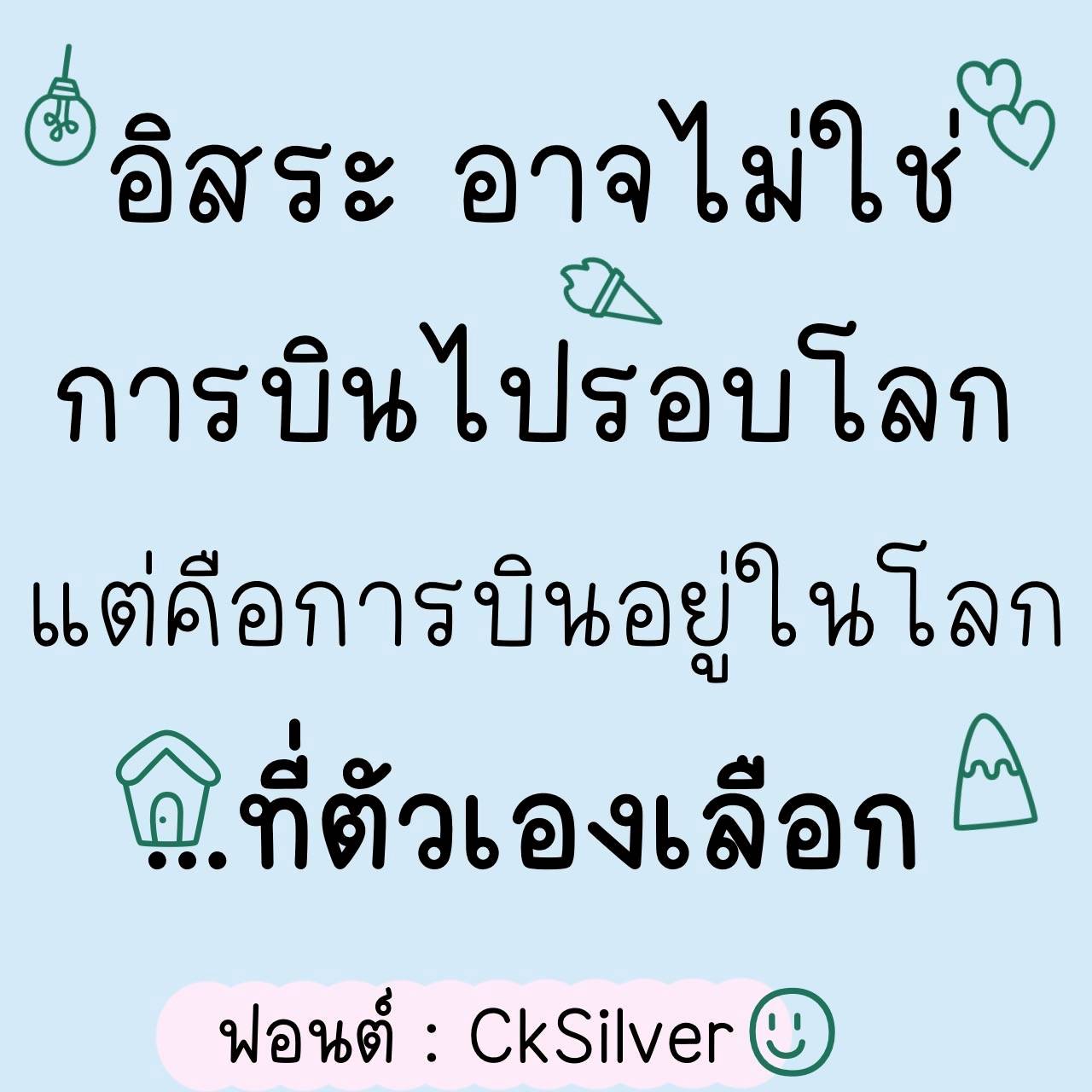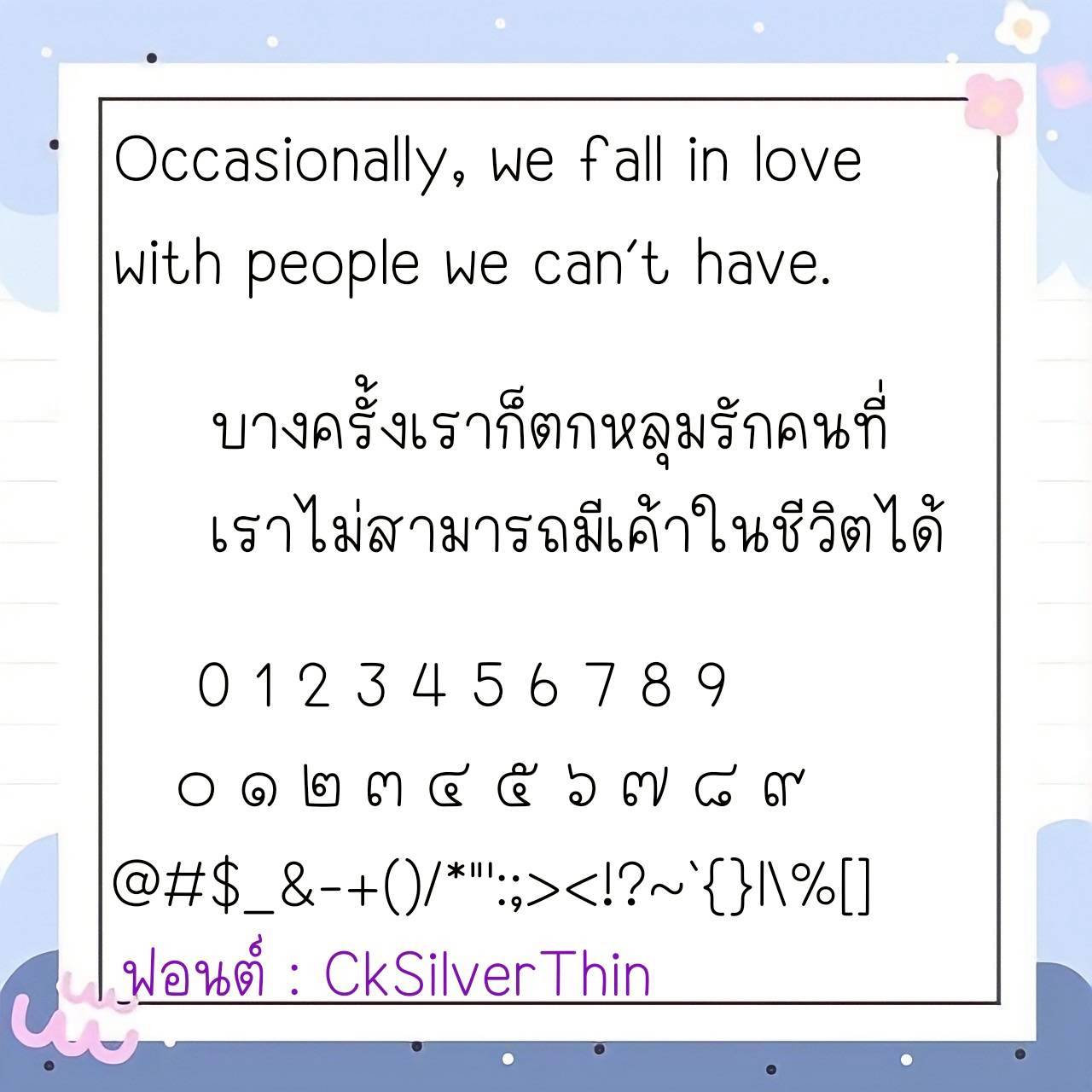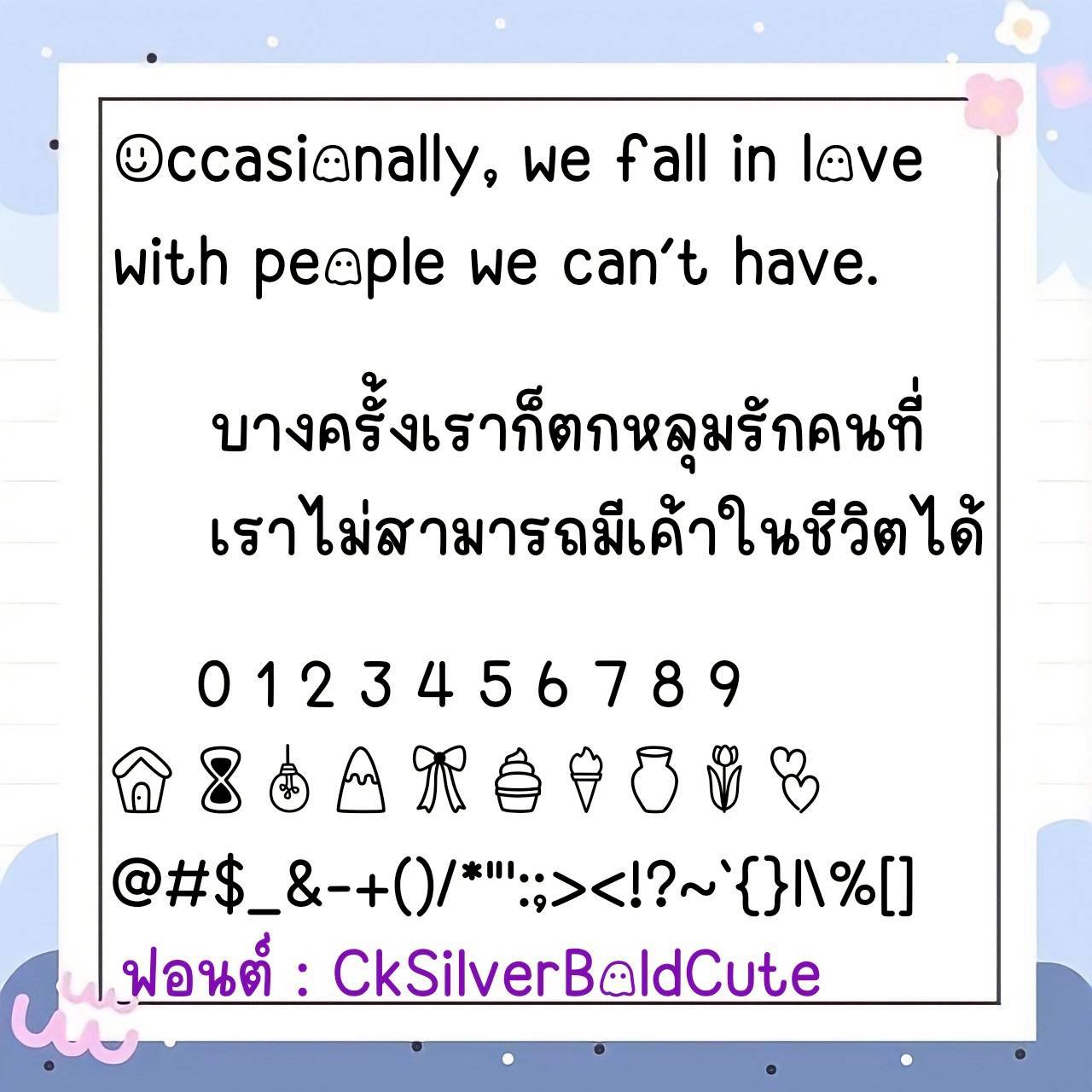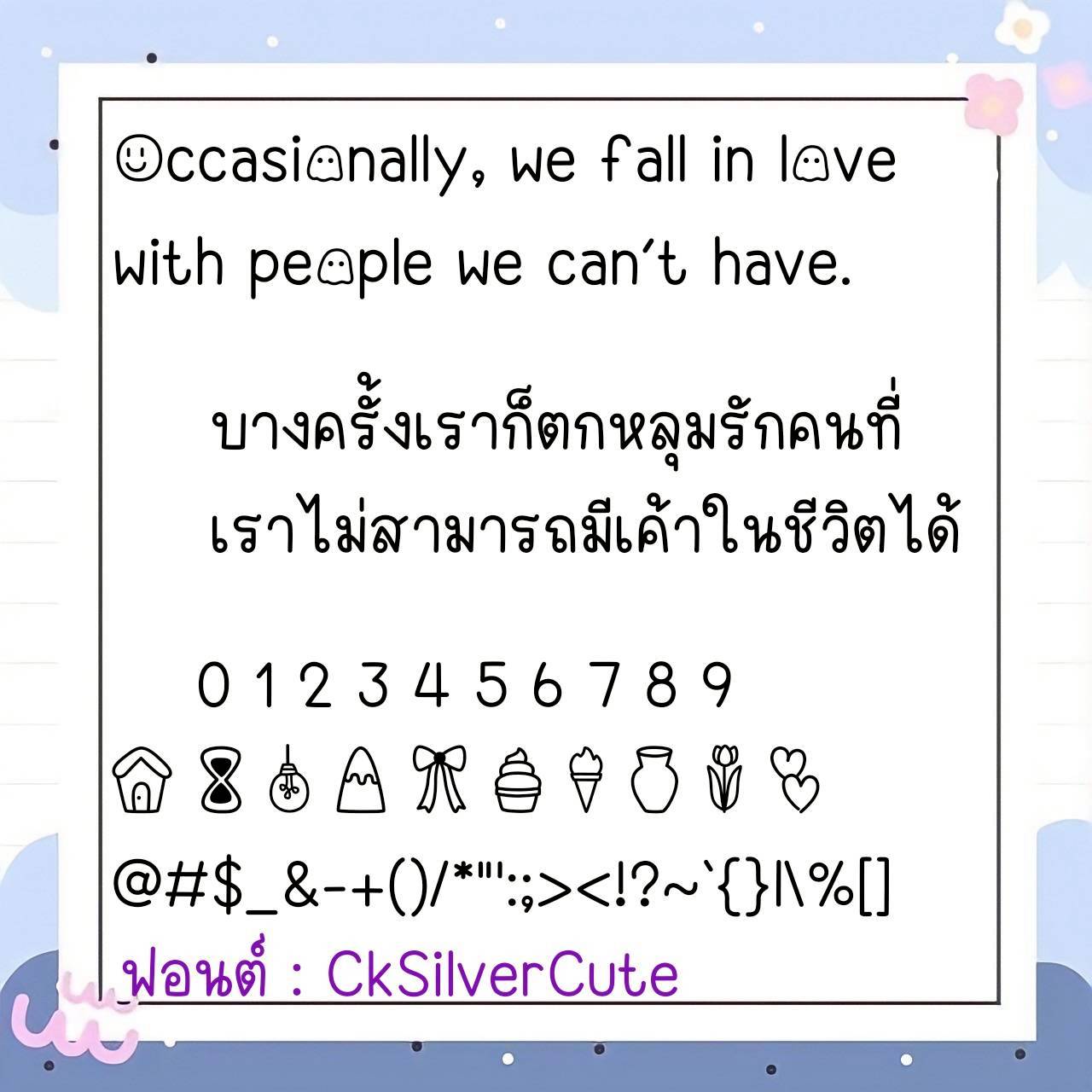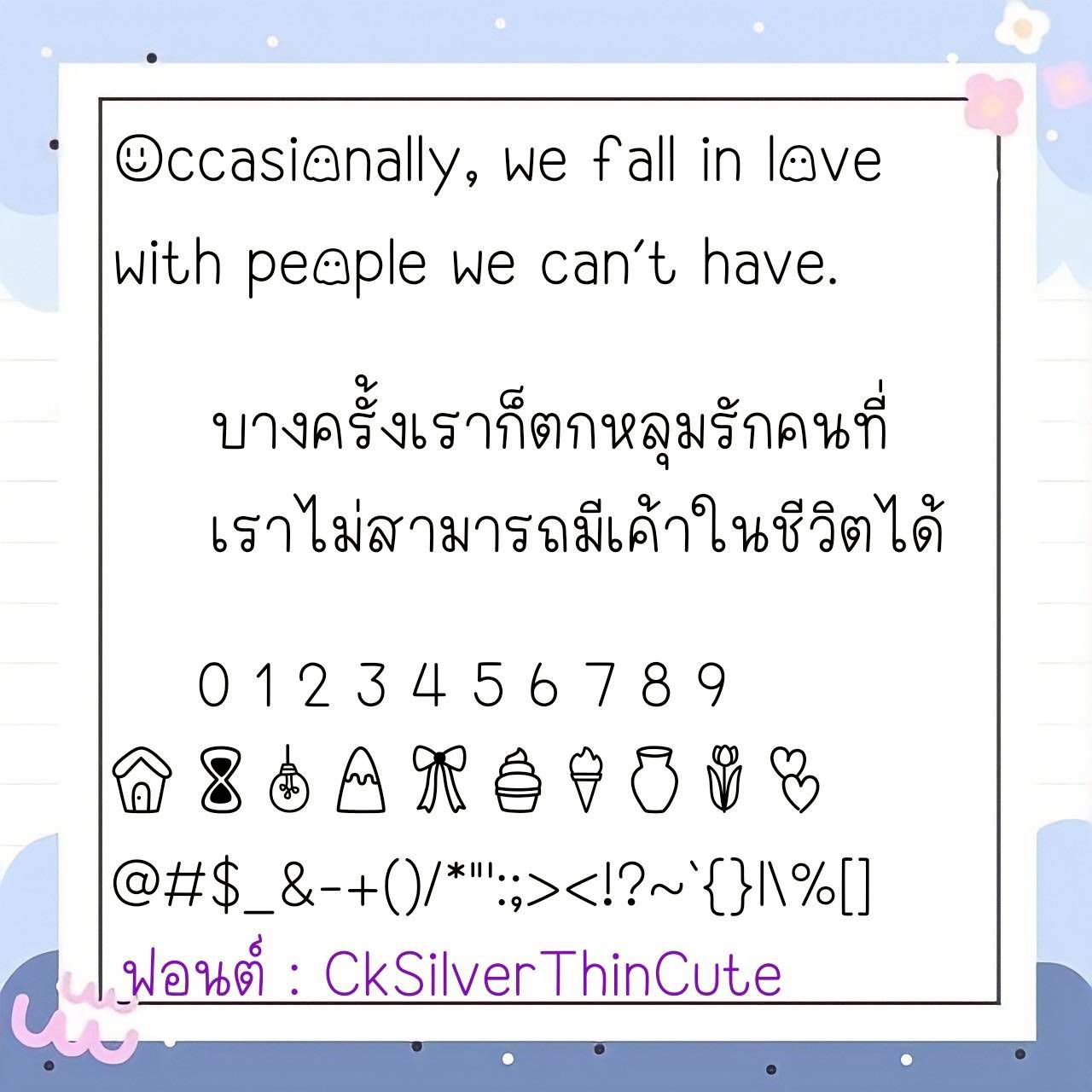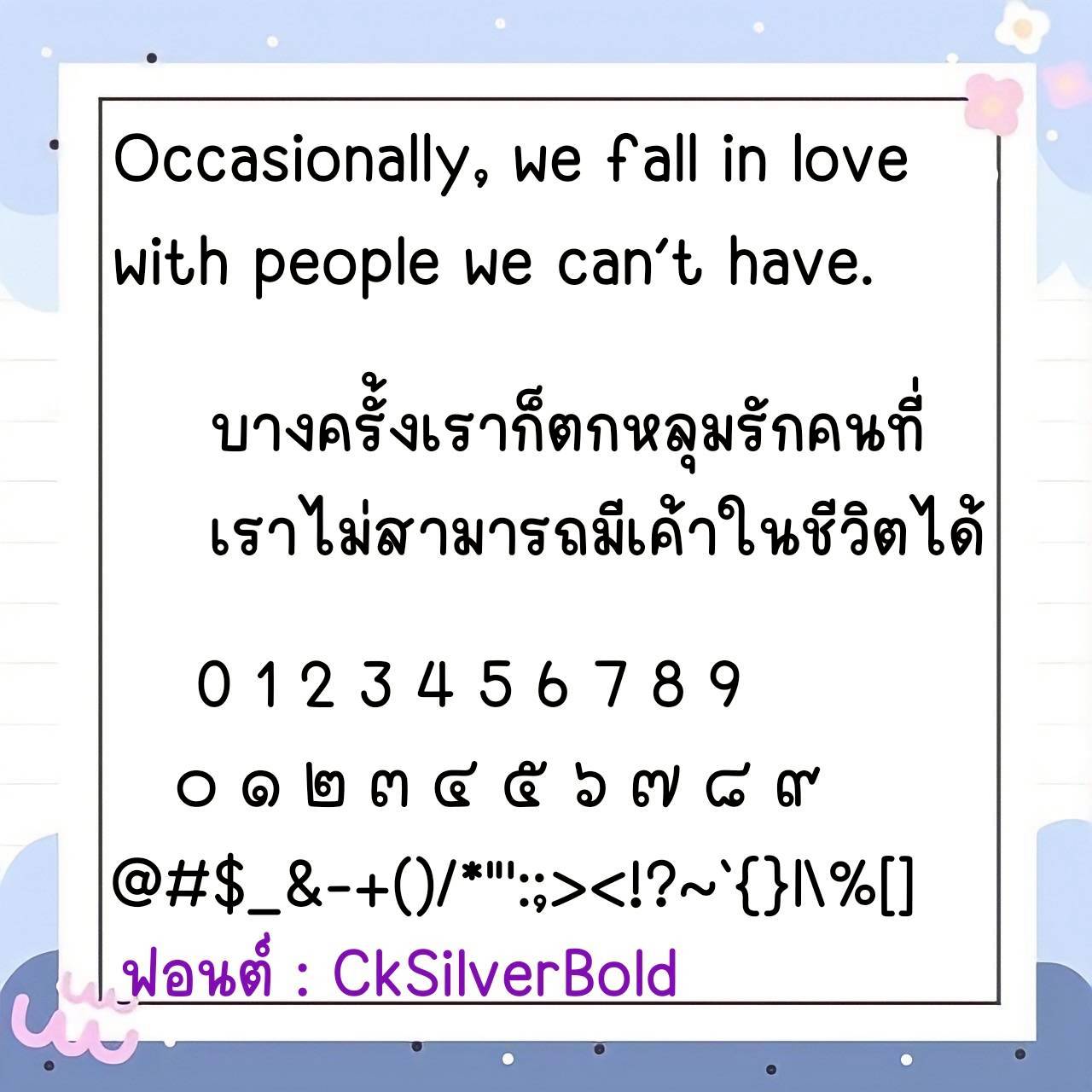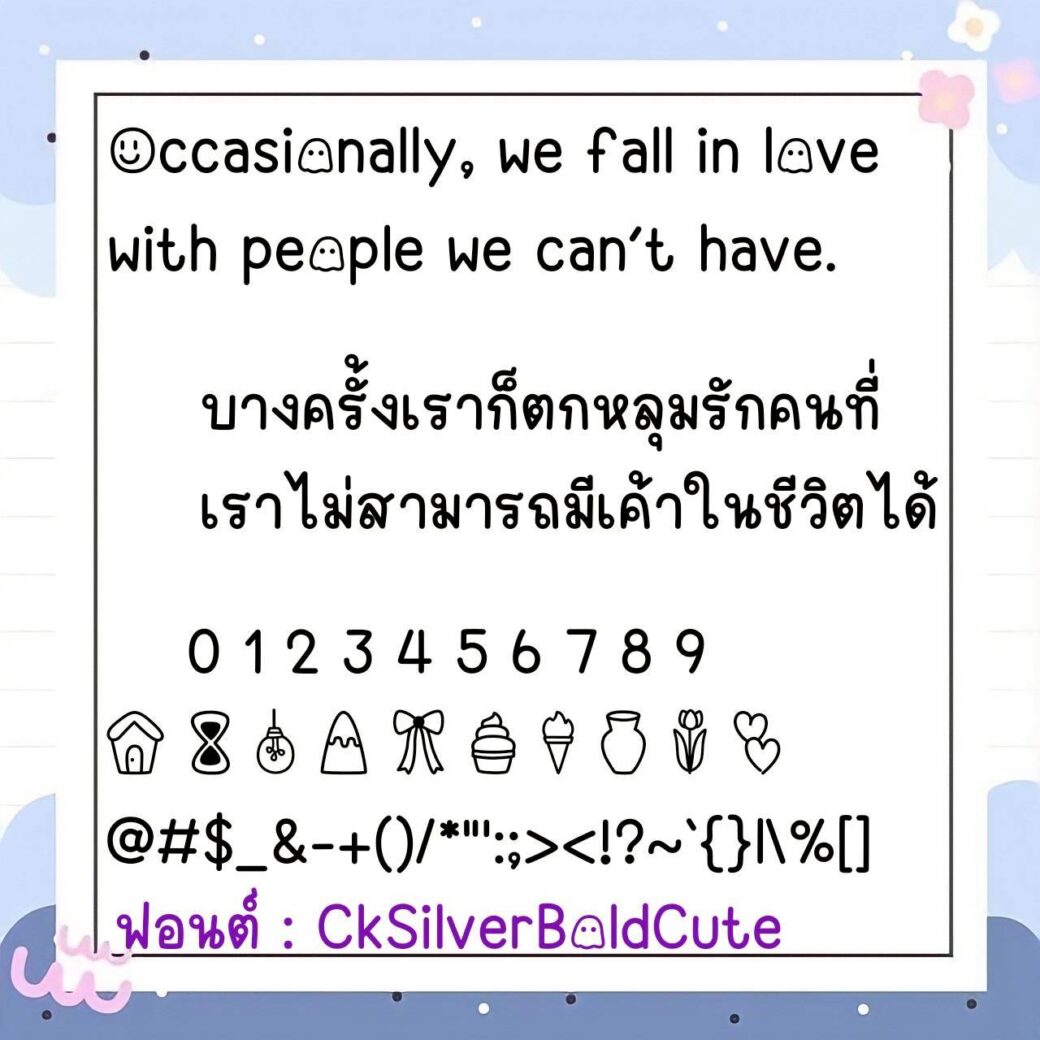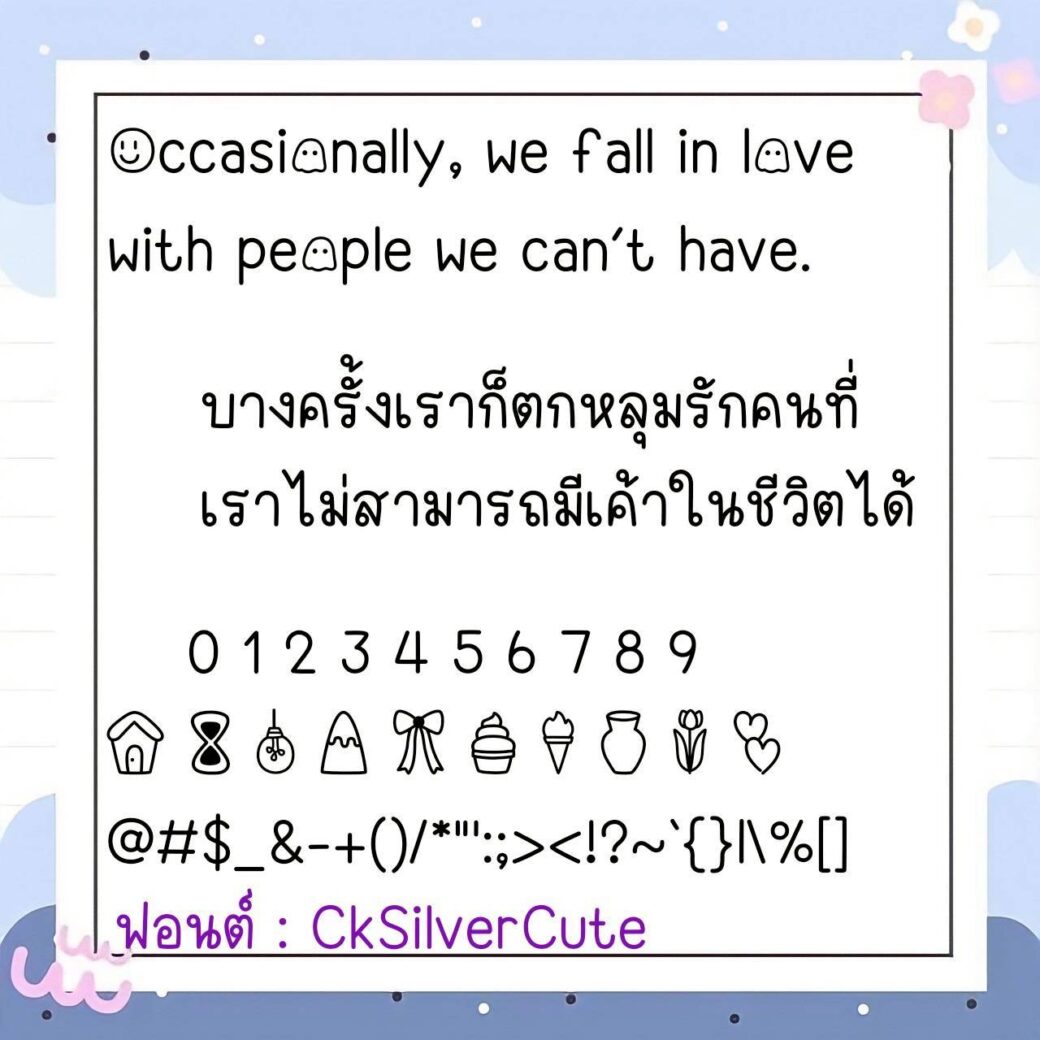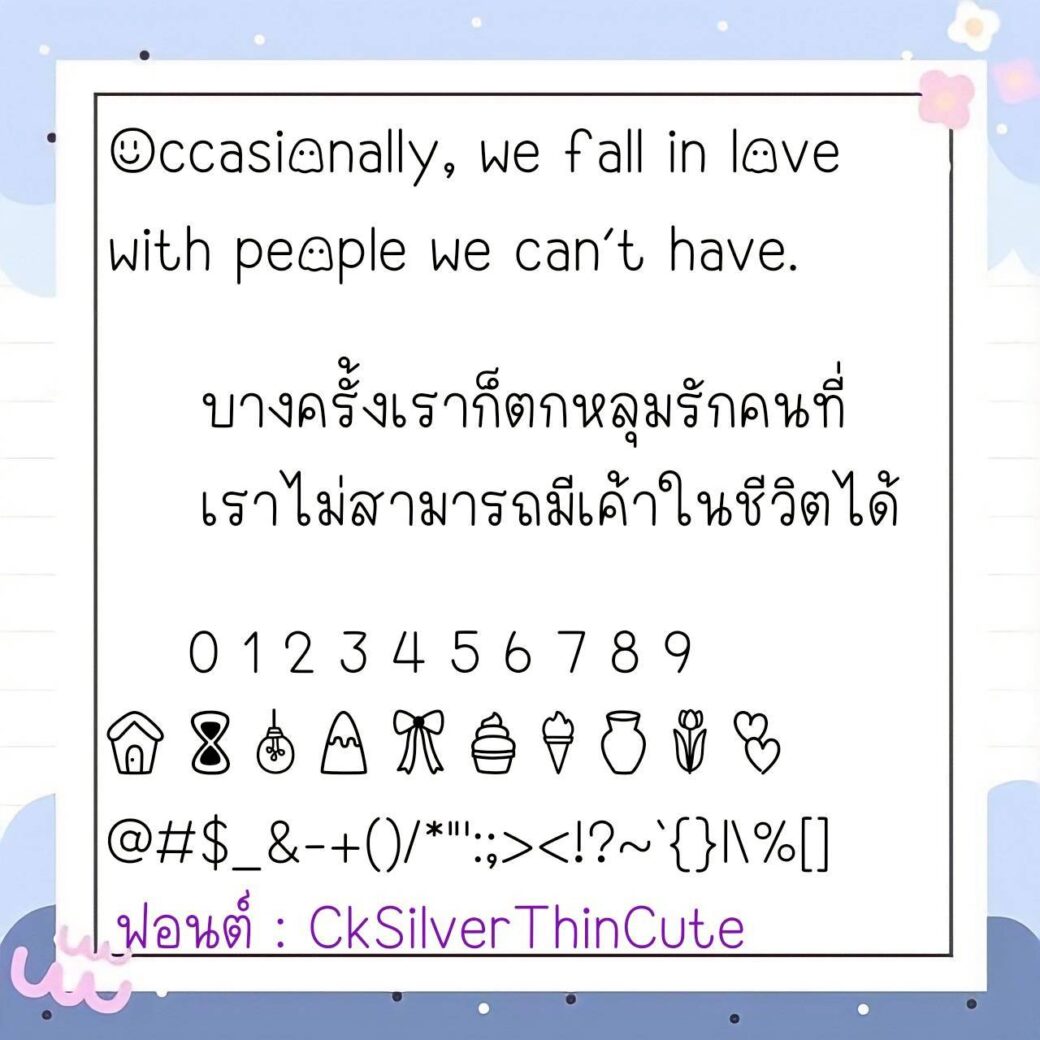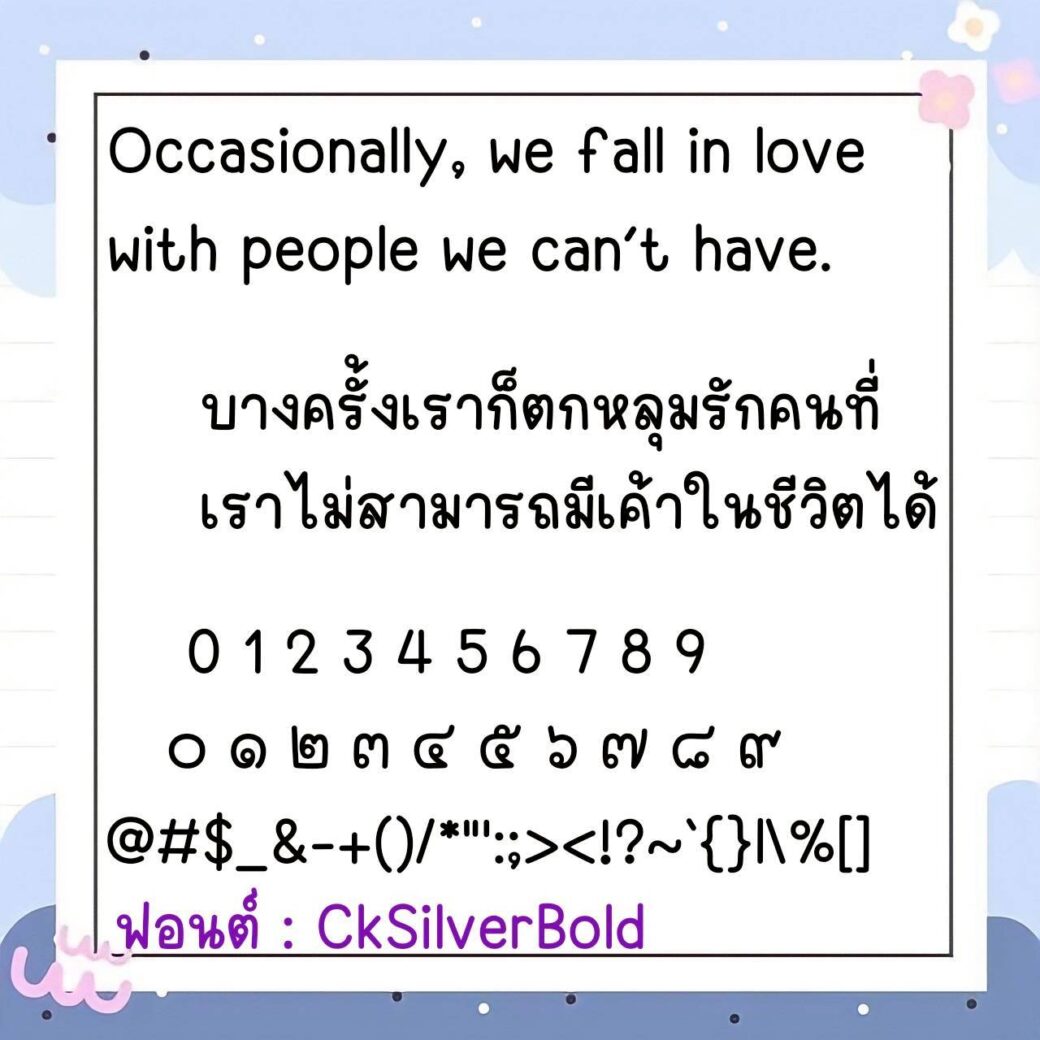
Font CkSilver
🔸 ฟอนต์ลายมือแนวน่ารัก กึ่งเรียบร้อย แต่ยังดูมีความน่ารักวัยรุ่น ขนาดตัวพอดีๆเน้นอ่านง่าย และยังมีไฟล์อิโมจิน่ารักๆที่ใช้แทนเลขไทยให้ด้วยค่ะ 🥰💙
🔹 A cute, semi-formal handwritten font with a youthful, adorable feel. The size is just right for easy reading, and it also includes cute emojis to replace Thai numerals. 🥰💙
🔸ฟอนต์ลายมือแนววัยรุ่น มีความยึกยัก น่ารักมีสไตล์ดูมีลูกเล่น ดูไม่น่าเบื่อ และยังมีไฟล์อิโมจิน่ารักๆที่ใช้แทนเลขไทยให้ด้วยค่ะฟอนต์ปรับสระเรียบร้อยไม่ลอย ไม่เหลี่ยม ใช้งานได้กับทุกโปรแกรม ได้ทั้ง ios(รองรับกับแอพต่างๆที่รองรับฟอนต์ในios เช่น Goodnote, Procreate)/android/คอมฯ/Ps/Word,Excel ได้หมดจ้าาาาา❤️❤️❤️